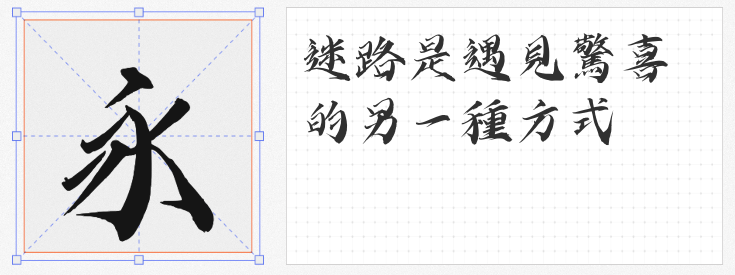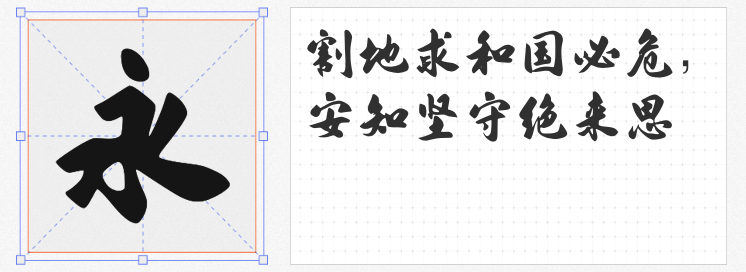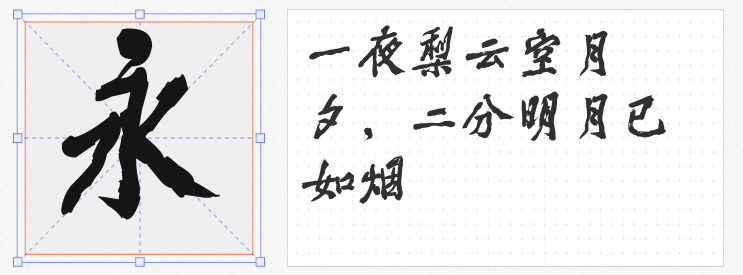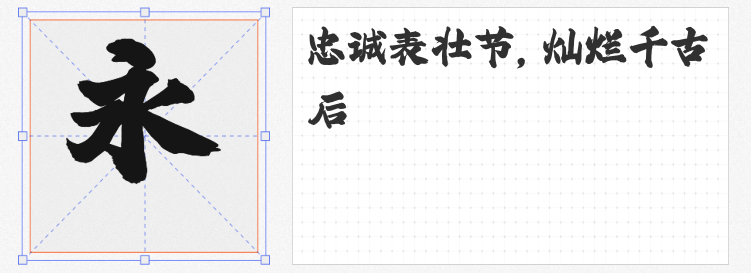
在传统与现代交融的文创设计领域,一款契合主题的字体往往能成为点睛之笔。本文精选四款兼具艺术性与实用性的免费商用毛笔手写字体,助您轻松打造古风雅韵的视觉盛宴。
1. 字屿云游手书
这款字体以行云流水的笔触勾勒出剑气与流云的交融之美。露锋用笔贯穿始终,结体紧致而不失灵动,曲线张弛间暗藏锋芒。其独特之处在于将阴柔婉转与阳刚遒劲完美平衡,既适合印章、书签等传统器物设计,亦能为现代国潮插画增添飘逸锐劲的视觉张力。
2. 余思源颜黄体
融合颜真卿的筋骨厚重与黄庭坚的长枪大戟,这款行楷字体以"浑厚洒脱"为魂。外拓笔势与舒展撇捺彰显盛唐气象,飞白处理又赋予数字时代的呼吸感。支持中英希腊等多语言符号系统,从古籍装帧到品牌LOGO,从茶器包装到数字艺术展,皆能演绎出传承与创新的双重韵律。
3. 字体家AI造字霸行
由AI神笔与叶根友字体联袂打造,这款智能字体突破传统书写的物理局限。算法模拟的飞白效果与笔锋转折,既保留人工书写的温度感,又具备工业设计的精准度。特别适合需要规模化应用的文创场景,如连续图案背景、动态字体特效等数字化创作。
4. 飞波正点体
以"稳重如山,气势如虹"为设计理念,这款字体通过加粗笔画与上扬笔锋构建出强烈的视觉冲击力。从电影海报到游戏品牌,从户外广告到电商主图,其百搭属性使其成为商业设计中的"重型武器",尤其适合需要强化记忆点的文化IP开发。